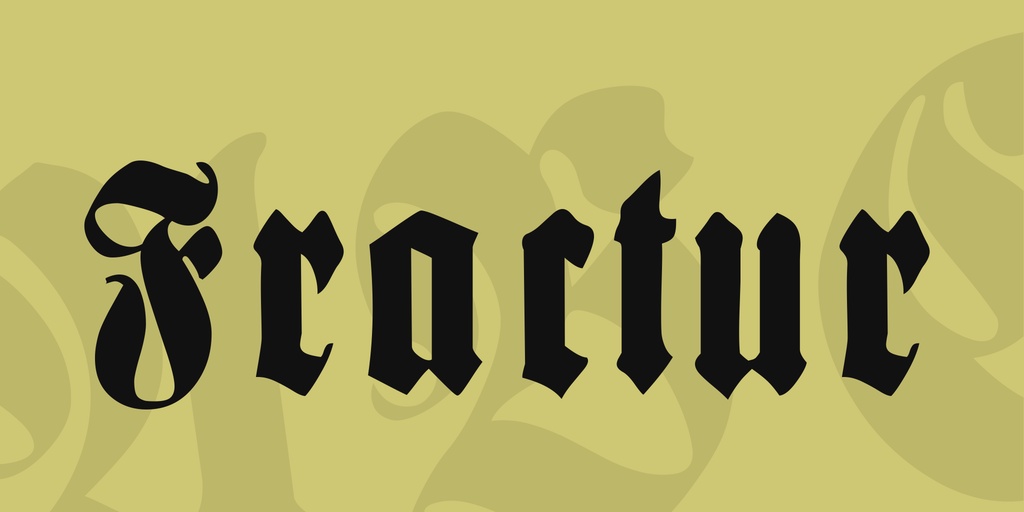
Fractur Font
Na categoria de fonts Display, a Fractur Font é uma escolha incrível para dar seu design um toque distintivo e moderno, ideal para trabalhos que exigem destaque visual imediato. Desenhada pelo talentoso Hamilton, essa font traz em seus traços uma mistura elegante e arredondada de linhas góticas e romanas, com certa dose de descontração proporcionada por elementos fracturados. A Fractur Font é perfeita para quem busca um contraponto suave à linguagem tradicional e moderna. Ela permite que você personalize seu design com uma personalidade única, capaz de destacar seu conteúdo em qualquer mídia digital ou impressão. Não importa se você está criando materiais para o mercado financeiro, design gráfico, comunicação visual ou qualquer outro campo – a Fractur Font oferece os recursos adequados para que seus projetos ganhem destaque. Com um toque de originalidade e uma aparência sofisticada, essa font é ideal para designers buscando um meio de expressar sua criatividade em um design mais chamativo. Combinadas com cores vibrantes ou elementos de tipografia minimalistas, a Fractur Font se assegura de que seu conteúdo seja o centro de atenção. Não hesite em experimentá-la; ela não só enriquecerá suas criações, mas também irá tornar sua marca ainda mais impactante e memorável.